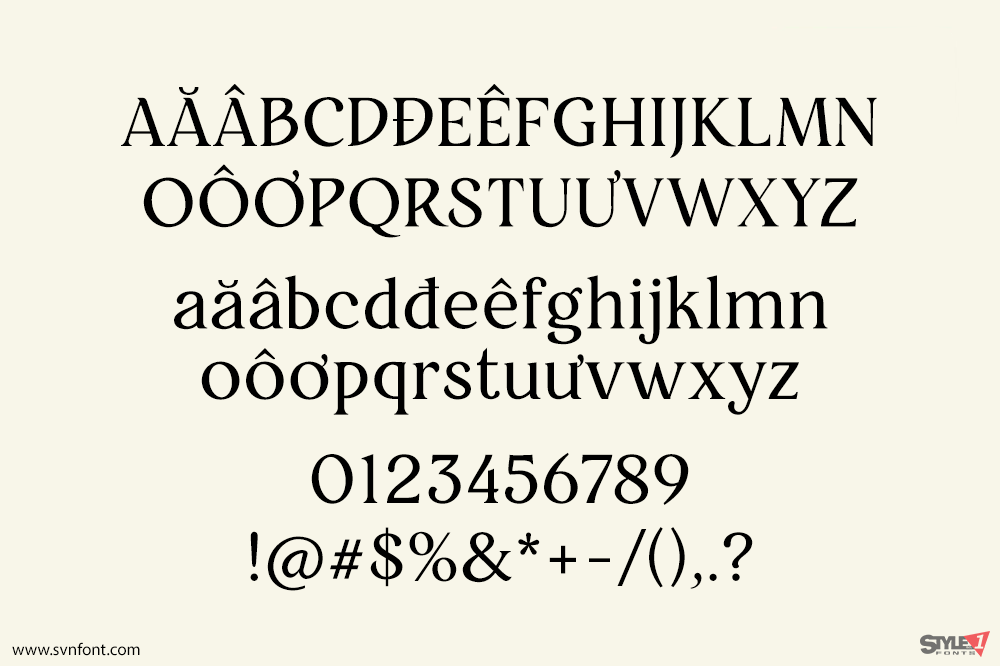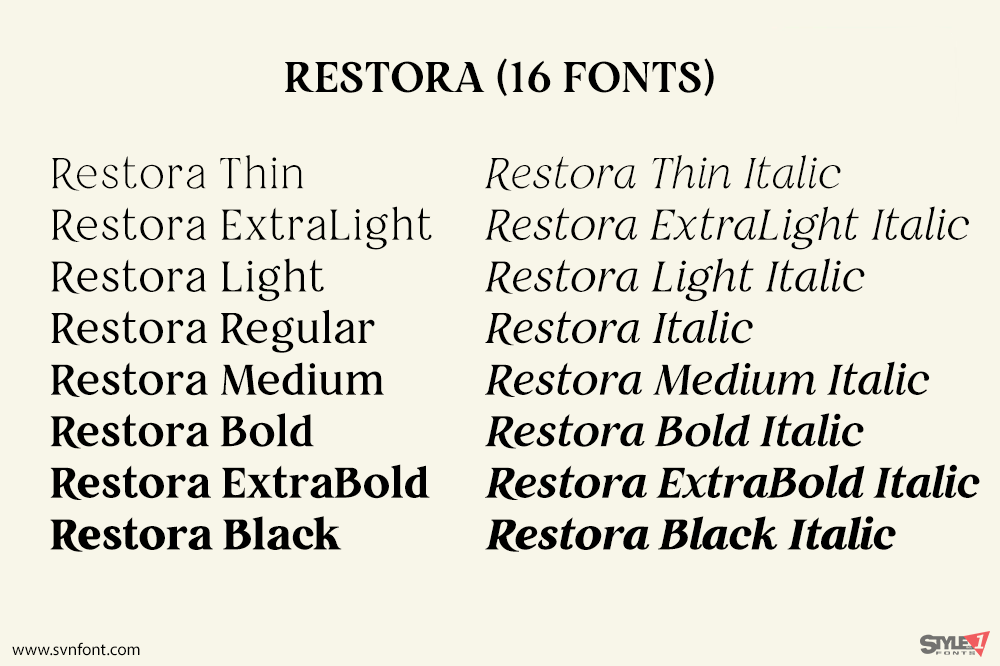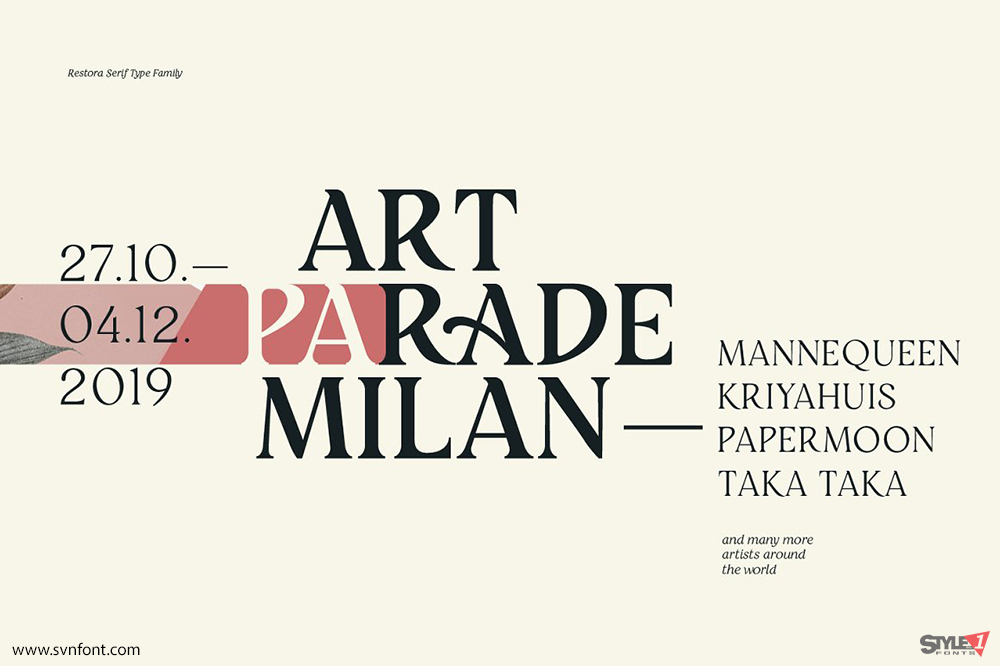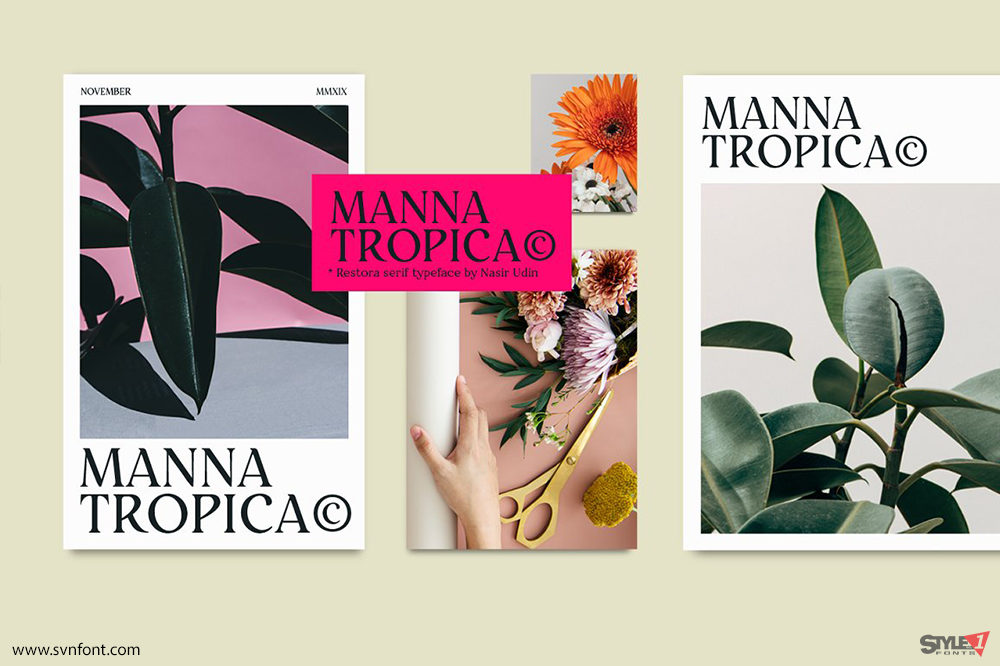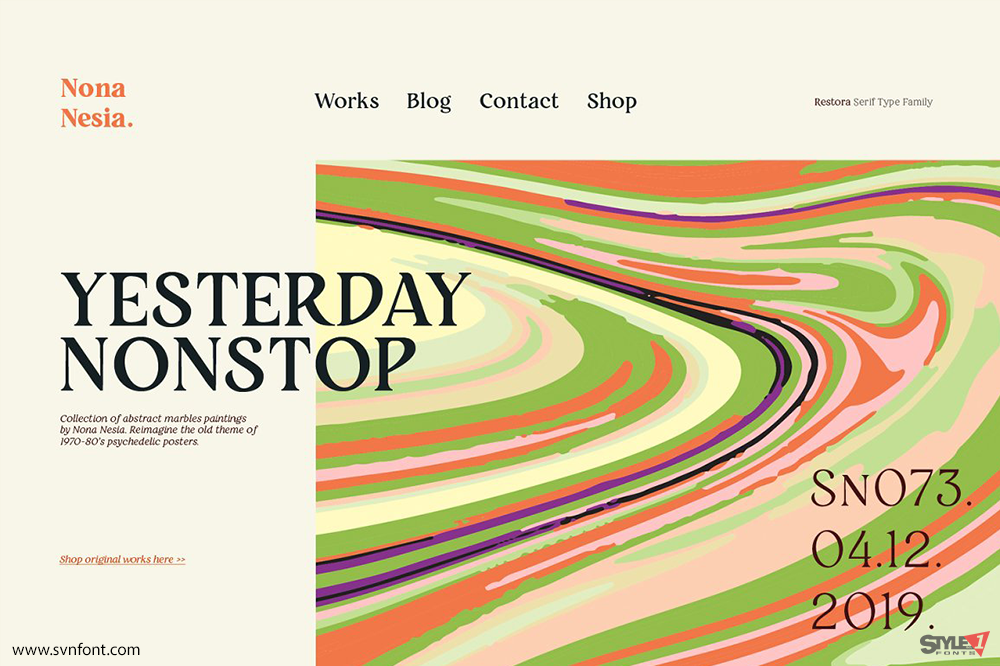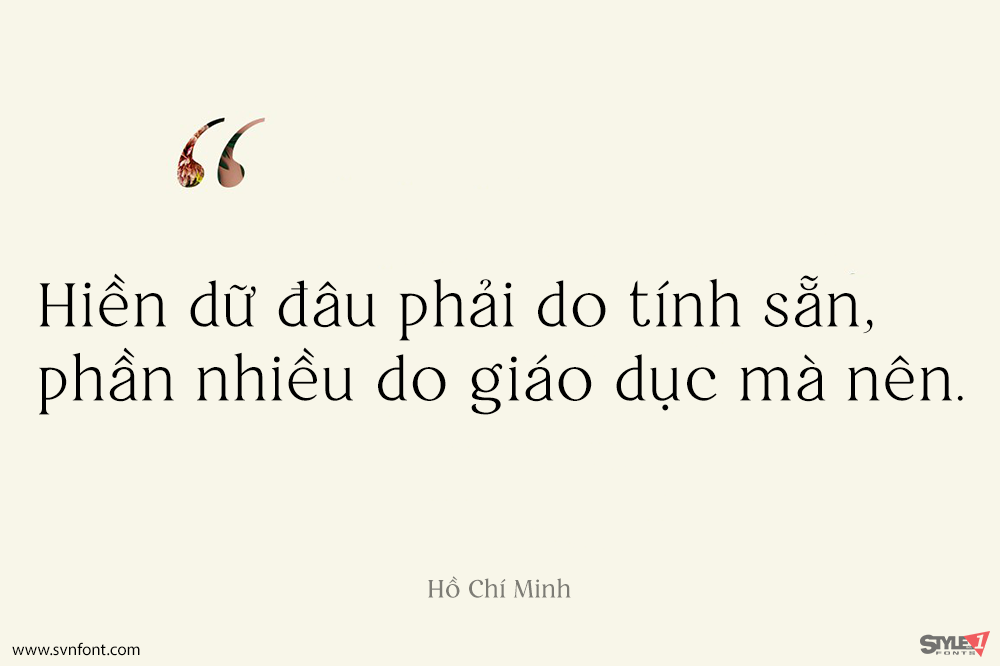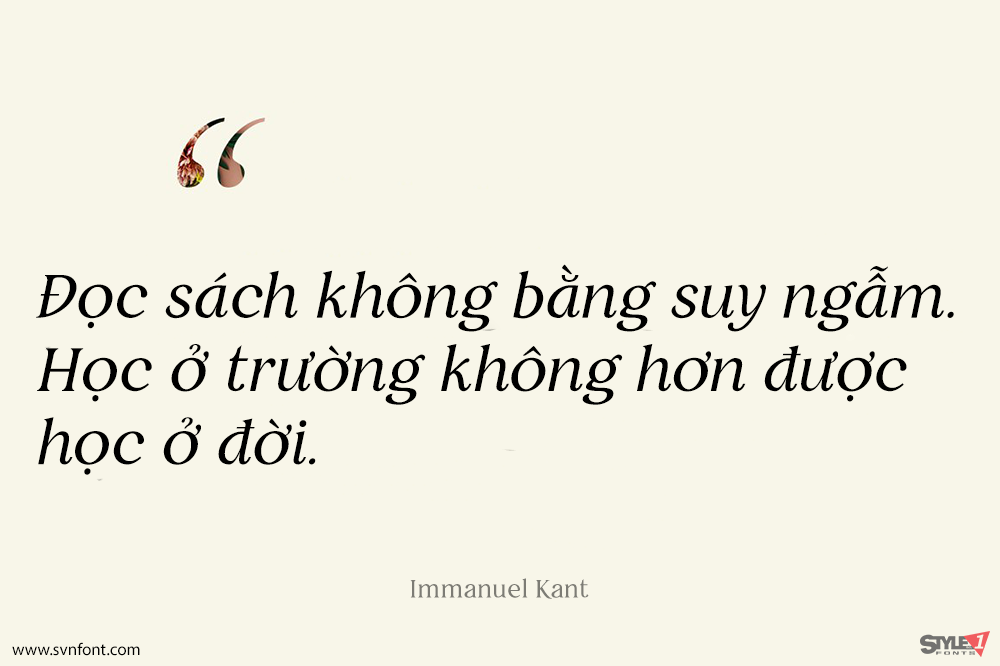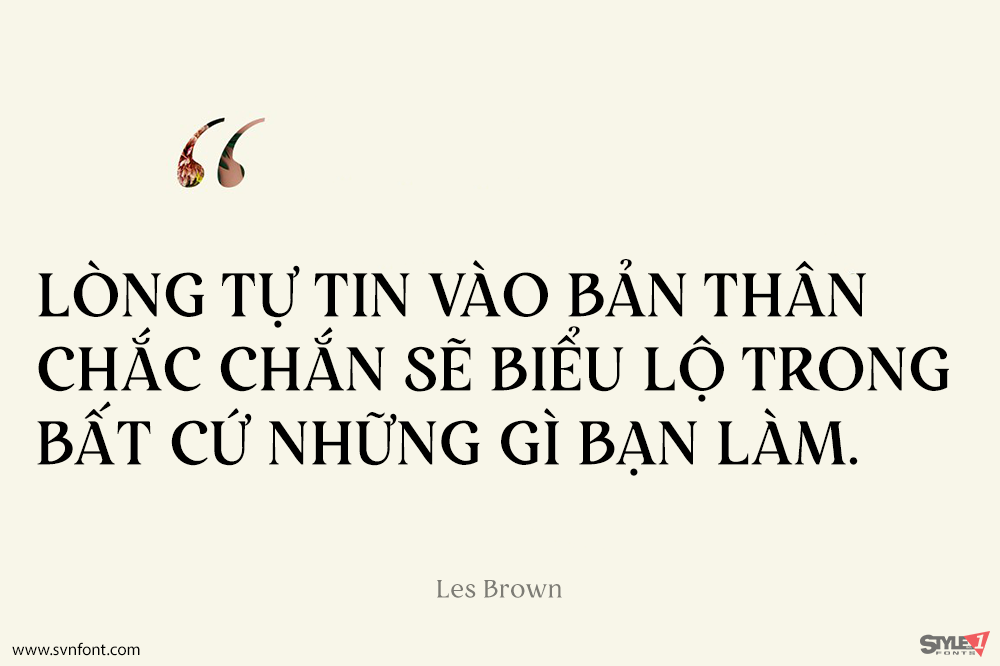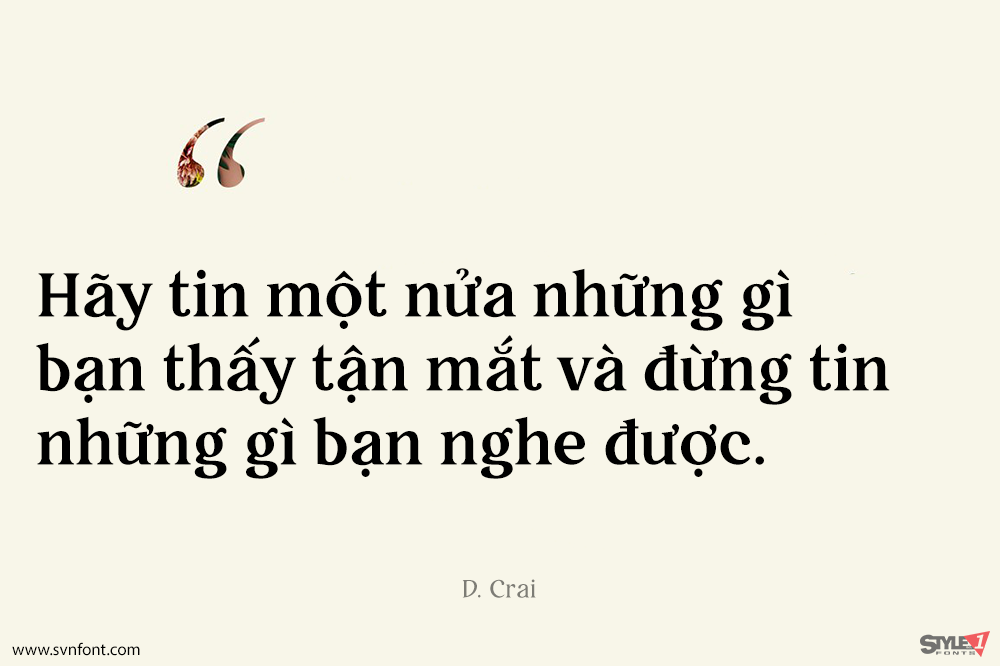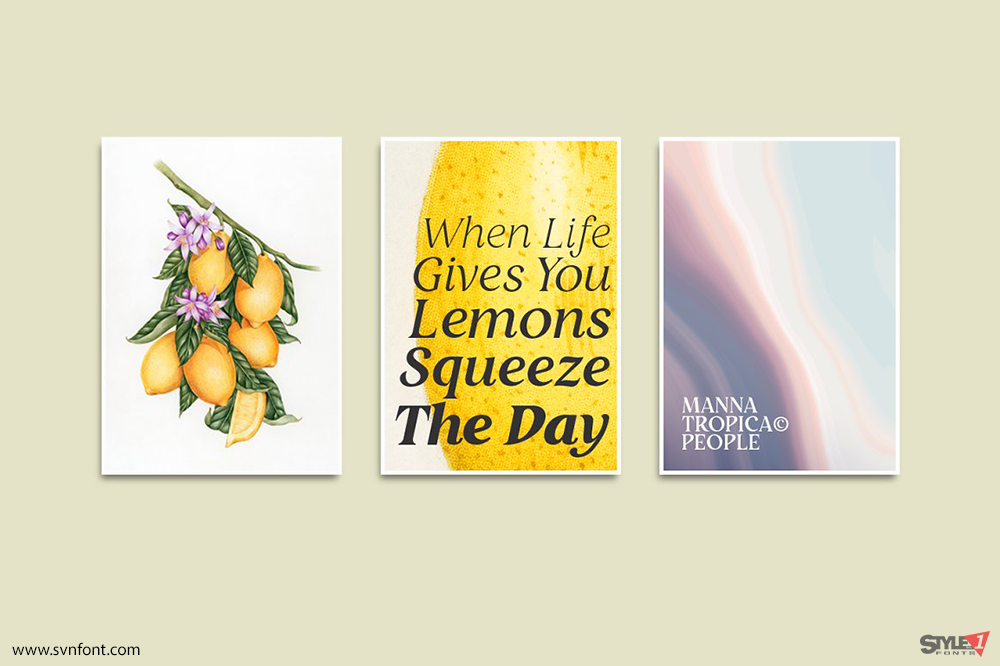
Restora là sự kết hợp của các kiểu chữ serif roman kiểu cũ. Sự pha trộn giữa các hình dạng chữ đẹp và phông serif kiểu cũ biến Restora thành một bộ phông chữ linh hoạt có thể sử dụng trong nhiều chủ đề thiết kế khác nhau.
Phông chữ này có tám độ đậm từ thin đến black, cùng với các kiểu chữ nghiêng tương ứng. Sự đa dạng về độ đậm cung cấp nhiều lựa chọn phong cách, giúp bạn tìm thấy cảm hứng phù hợp nhất cho dự án của mình, từ văn bản chính đến các tiêu đề lớn, từ phong cách cổ điển đến hiện đại và táo bạo.
Restora rất thích hợp cho bìa sách, ấn phẩm biên tập, xây dựng thương hiệu, quảng cáo và nhiều hơn nữa. Các tính năng OpenType của nó cung cấp nhiều ký tự trang trí, chữ ghép đẹp mắt và các ký tự thay thế theo phong cách (stylistic alternates) mang đến cho tác phẩm của bạn một vẻ ngoài độc đáo.
Nhà thiết kế: Nasir Udin
Nhà phát hành: Nasir Udin